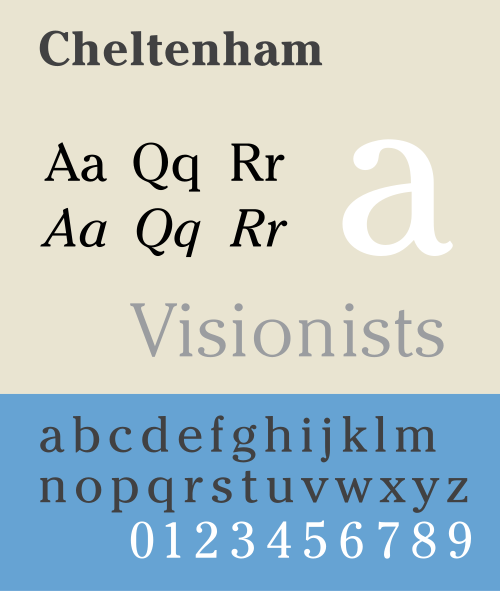
| カテゴリ | セリフ |
| 分類 | 古いスタイル |
| デザイナー | バートラム・グロブナー・グッドヒュー ジョセフ・W・フィニー |
| 鋳造所 | アメリカンタイプファウンダーズ |
| リリース日 | 1903 |
チェルトナムは、 1896年に建築家バートラム・グッドヒューとチェルトナム・プレスのディレクターであったインガルス・キンボールによって設計された展示用の書体です。オリジナルの図面はボストン・オールド・スタイルとして知られ、高さ約14インチで作られました。これらの図面はその後、アメリカン・タイプ・ファウンダーズ(ATF) のモリス・フラー・ベントンに引き渡され、最終的なデザインに発展しました。試作品は1899年に早くも作られましたが、書体は1902年まで完成しませんでした。書体は1904年にキンボールによって特許を取得しました。後に、基本書体はモリス・フラー・ベントンによって広範な書体ファミリーに展開されました。[1]
チェルトナムは、単一の歴史的モデルに基づいているわけではなく、アーツ・アンド・クラフツ運動の影響が見られます。もともとテキスト書体として意図されていた「チェルト」は、「ディスプレイ書体の王様」として大成功を収めました。この書体が大人気の理由の1つは、古いスタイルと過渡期の書体の両方の要素を持っているため、チェルトナムの見出しは事実上あらゆる体型にマッチするからです。[2]ディスプレイ目的の書体の圧倒的な人気は、 1930年代の 幾何学的なサンセリフ書体 の出現まで続きました。
鋳造タイプ
鋳造型では以下のバージョンが利用可能であった: [3]
- ATFの チェルトナムシリーズ
- チェルトナム(1903 年、バートラム・グッドヒュー、インガルス・キンボール、モリス・フラー・ベントン、および/またはジョセフ・W・フィニー)
- チェルトナム ボールド(1903、モリス フラー ベントン)
- チェルトナム ボールド コンデンスド(1904、モリス フラー ベントン)
- チェルトナム ボールド イタリック + チェルトナム ボールド コンデンス イタリック + チェルトナム ワイド + チェルトナム ボールド アウトライン(1905、モリス フラー ベントン)
- チェルトナム ボールド エクストラ コンデンス + チェルトナム ボールド エクステンデッド(1906、モリス フラー ベントン)
- チェルトナム インライン + チェルトナム インライン エクストラ コンデンス
- チェルトナム インライン エクステンデッド(1907、モリス フラー ベントン)
- チェルトナム オールドスタイル コンデンス + チェルトナム ミディアム(1909、モリス フラー ベントン)
- チェルトナム ミディアム イタリック + チェルトナム エクストラ ボールド(1910 年、モリス フラー ベントン)
- チェルトナム ボールド シェード + チェルトナム ボールド イタリック シェード + チェルトナム エクストラ ボールド シェード(1912 年、モリス フラー ベントン)
- チェルトナム ミディアム コンデンス + チェルトナム ミディアム エクスパンデッド(1913、モリス フラー ベントン)
- ベネチアン(1911年、モリス・フラー・ベントン)は元々チェルトナム#2と呼ばれていましたが、オリジナルの顔との類似性はわずかでした。
- Linotype、Monotype、Ludlow はすべて、その名前で独自のCheltenham を生産しており、ATF とほぼ同じ数のバリエーションがあります。いくつかの新しいバリエーションが追加されました。
- チェルトナム筆記体(R.ハンターミドルトン、ラドロー)
- チェルトナム ワイド イタリック( Sol Hess、モノタイプ)
- インタータイプは彼らのバージョンをチェルトニアンと呼んだ
- ウェスタン・タイプ・ファウンドリーは、そのバージョンをチェスターフィールドと呼んだ。
- ハンセンタイプファウンドリーは彼らのバージョンをクラフトマンと呼んだ
- インランド・タイプ・ファウンドリーは自社のバージョンをケニルワース(1904)と名付けた。
- キーストーンタイプファウンドリーは自社のバージョンをローウェルと名付けた(1905年、チャールズ・W・スミス)
- スティーブンソン・ブレイクは彼らのバージョンをウィンチェスターと呼んだ
- イギリスのモノタイプ社は自社のバージョンをグロスターと名付けた。
- ベルトルトは彼らのバージョンをソルボンヌ(1905)と呼んだ。
コールドタイプバージョン
チェルトナムの人気はコールドタイプ時代も根強く、様々なメーカーから以下の名前で販売されました。[4]
コールドタイプの変種であるITC Cheltenham も、 1975 年にInternational Typeface Corporationのために Tony Stan によってデザインされました。このフォントは、より大きなx ハイトと改良されたイタリック体の詳細を特徴としています。このファミリーには、それぞれ 4 つのウェイトと 2 つの幅があり、補完的なイタリック体があります。
デジタル版
オリジナルの書体は現在の所有者であるKingsley/ATFによってデジタル化され、Bitstream Incによって販売されています。ITC 版はLinotype、Monotype、Adobe Systemsからも入手可能で、 Ed Benguiatがデザインしたハイライト付きの 1993 年版 ITC Cheltenham Handtooled も販売されています。他のバージョンは Tilde、 Font Bureau、URW++、 Scangraphic Digital Type Collection、Elsner+Flakeから入手できます。Besley Clarendon は HiH から入手できます。Monotype は Gloucester という名前でそのバージョンを提供しています。[5]
顕著な使用法
2003年、ニューヨークタイムズは、印刷版の見出しに使用するために、より統一されたチェルトナム書体のパレットを導入しました。それ以前は、チェルトナムは、ビクトリア朝風の見出し書体の混合でサンセリフを含むいくつかの書体のうちの1つに過ぎませんでした。タイムズの副編集長兼デザインディレクターのトム・ボドキンは、書体デザイナーのマシュー・カーターを雇い、使用中のラテンエクストラコンデンス書体のほとんど、およびブックマンとセンチュリーボールドの変種を置き換えるために、複数のウェイトと大幅にコンデンスされた幅のチェルトナムを作成しました。[6]
米国議会では、公に印刷されるすべての法案および決議の法案番号または決議番号はチェルトナムで設定されます。[7]この書体は、法案や法律自体にもタイトルやセクションの見出しを示すために使用されています。
Liturgical Press は、米国カトリック司教会議が米国のローマカトリック教区向けに 規定した典礼書に Cheltenham Bold 書体を使用しています。
IDGの「...for Dummies」シリーズのハウツー本は、ITC チェルトナムを舞台にしています。
LLBeanのロゴはチェルトナムに設置されています。
Akaiのロゴは ITC Cheltenham Ultra に設定されており、白い背景に赤い文字が描かれており、文字 A、K、A の ネガティブ スペースにキャンドル イメージ効果を生み出しています。
ヘルシンキの通り名の銘板はチェルトナムに設置されている。[8]
このフォントは日本の アニメ 『カウボーイビバップ』でよく使われており、特に各エピソードのエンディングカードでよく使われ、「See you Space Cowboy...」というフレーズが使われている[要出典]。
1992年から2000年まで、マース社はM&M'sキャンディーのフレーバー(プレーン、ピーナッツなど)の説明にこのフォントを使用していました。[9] [10]